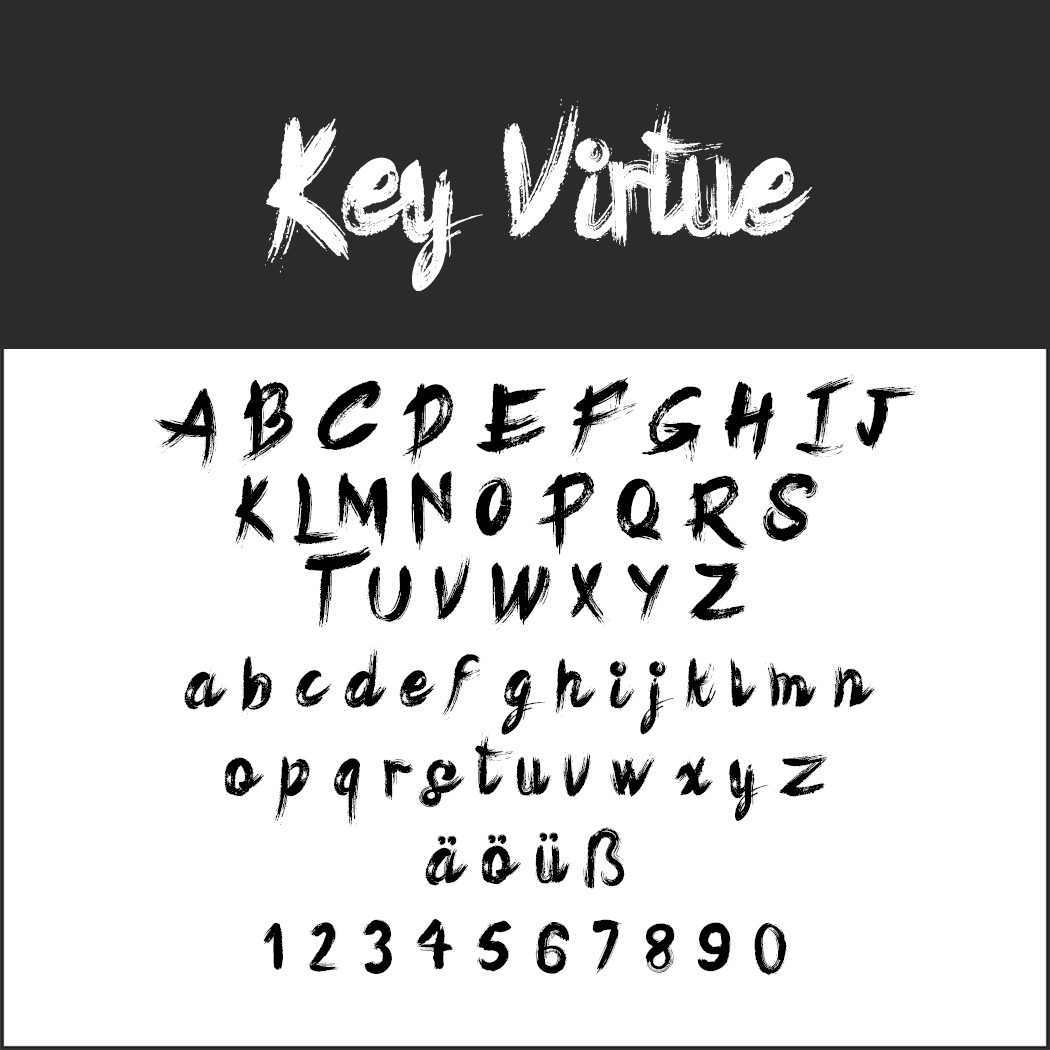
Eine Schreibschrift ermöglicht durch eine fortlaufende Linienführung flüssiges Schreiben von Hand. Ihr Einsatz signalisiert immer einen Bezug zu Menschen. Schreibschrift-Fonts wirken je nach Ausgestaltung und Verwendung emotional, lebendig, unkoventionell oder persönlich.
So wie im echten Leben jeder seine ganz eigene Handschrift entwickelt, haben wir in unserer Auswahl sehr unterschiedliche Stile zusammengestellt, die mal Schönschrift wiedergeben, mal wie von Hand Geschriebenes, teilweise mit unterbrochener Linienführung, das an Druckbuchstaben erinnert.
DK Hand
Wie mit Filzstift geschrieben und macht sich deshalb vor allem in imposanter Schriftgröße auf Plakaten gut. Eine Verbindung der einzelnen Buchstaben ist nur angedeutet.
Caveat
Pablo Impallari entwickelte diesen Font sowohl für kurze und längere Textblöcke. Zur Ergänzung gibt es noch einen Pinselstrich-Font: Caveat Brush.
Indie Flower
Hier ist alles rund und strahlt Harmonie aus. Die „hüpfenden“ Buchstaben unterstreichen den Handschrift-Charakter und machen längere Texte leichter lesbar. Streng genommen handelt es sich nicht um eine Schreibschrift, doch die einzelnen Buchstaben sind gewollt unregelmäßig und so eng beeinander, dass sie einen Schreibfluss suggerieren.
Key Virtue
Der Brush-Script-Font ist für den großen Auftritt gedacht. Den hat er am besten in kurzen Schlagwörtern auf einem Plakat.
Latina
Eben mal lässig auf einen Zettel hingeschrieben – genau so wirkt Latina. Passt, wenn es frisch und unkonventionell rüberkommen soll.
Parisienne
Elegant wie die Pariser Damenwelt trägt diese Schriftart ihren Namen zurecht. Kleine Unregelmäßigkeiten verstärken ihren unwiderstehlichen Charme.
Sacramento
Diese halbverbundene Schreibschrift orientiert sich am Stil der 1950er und 1960er Jahre, macht Überschriften zu einem Hingucker.
The Suavity
Hier werden Assoziationen an die charakterstarke Handschrift einer künstlerischen Seele wach. Geeignet für Titel und kurze Schlagwörter.
Satisfy
Klassische und moderne Elemente vereinen sich in dieser Pinselstrichschrift zu einem charmanten Font, der wegen ausgefallener Buchstaben jedoch auf kurze Textelemente beschränkt sein sollte.
Homemade Apple
Wie eine handschriftliche Notiz kommt Homemade Apple daher und macht sich – wie der Name schon andeutet – besonders gut bei handwerklich hergestellten Lebensmitteln und anderen in Handarbeit produzierten Dingen.